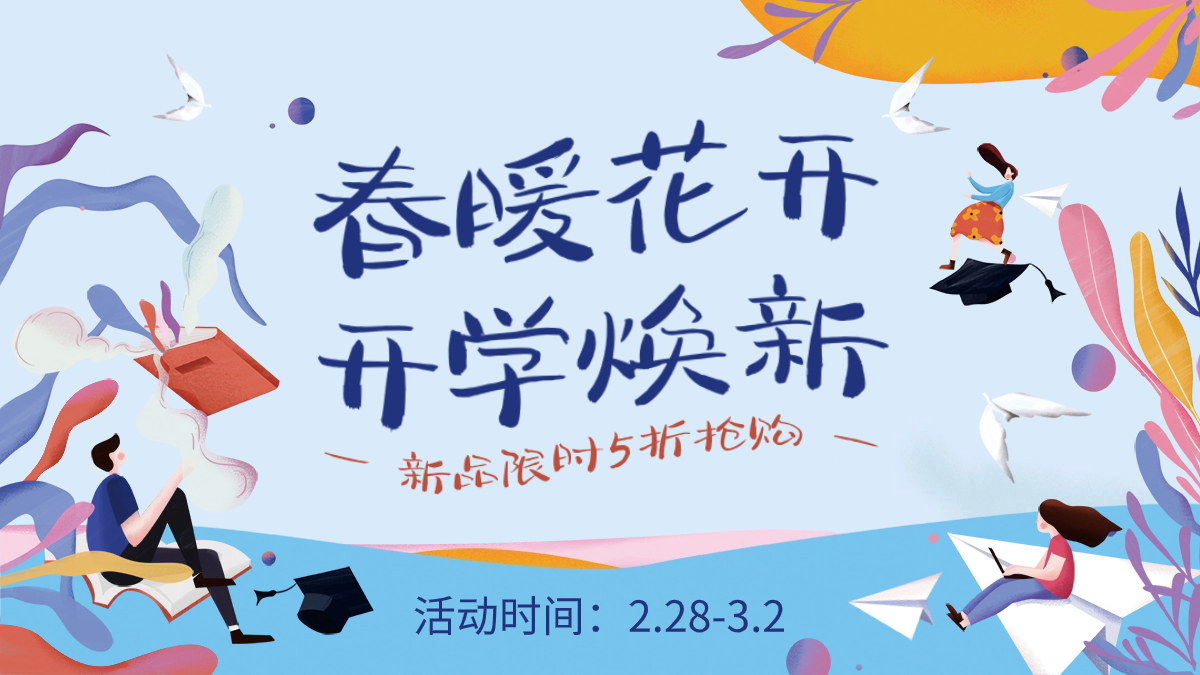
兵克清闲体
兵克清闲体,兵克清闲体,整体风格以清新雅致为主,既保留了传统书法的韵味,又融入了现代设计的元素,笔触设计柔和而流畅,宛如微风拂过水面,带给人一种轻松愉悦的感受。在保持独特风格的同时,也注重了可读性的提升。字体的间距、行距等排版参数都经过精心调整,以确保在各种屏幕与媒介上都能呈现出清晰、易读的视觉效果。应用场景:文学作品与诗集、休闲旅游宣传、社交媒体、品牌与包装设计等。